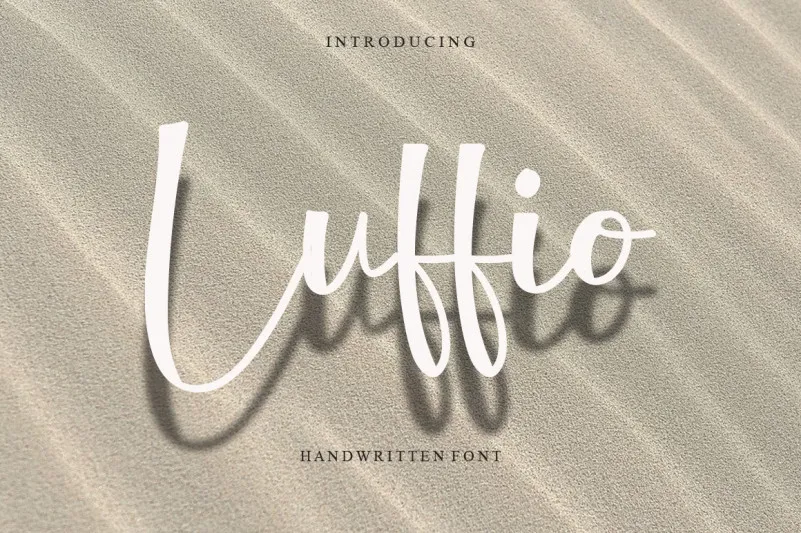
Luffio Font – Download Grátis
A Luffio Font é uma elegante escolha para os designers que buscam um touch delicado e criativo nas suas criações digitais. Seja você um amante de redes sociais procurando pela perfeita mistura entre personalidade e simplicidade ou um artesão dedicado ao DIY, essa fonte única se adapta às mais diversas ideias de projeto. Suas linhas atraentes e desenhos leves são tão versáteis quanto a criatividade humana, permitindo que qualquer ideia inovadora seja transformada em arte. Com uma mistura perfeita de funcionalidade e design elegante, a Luffio é o complemento ideal para quem busca expressar sua personalidade através das telas digitais.